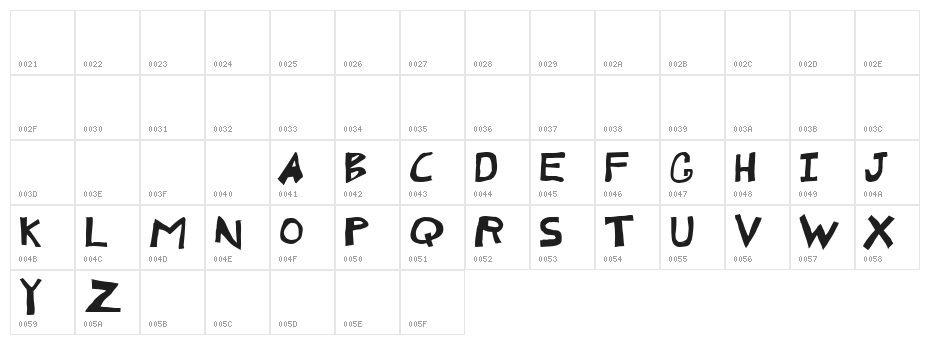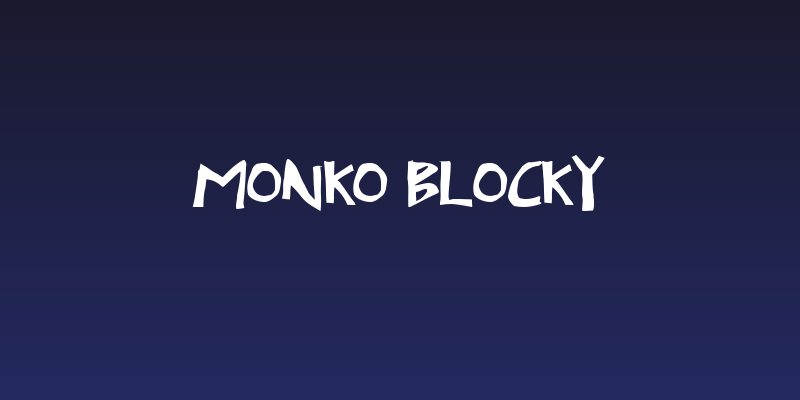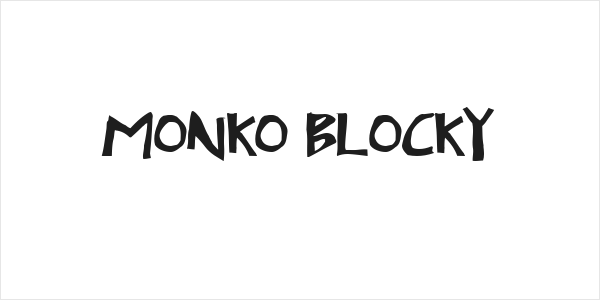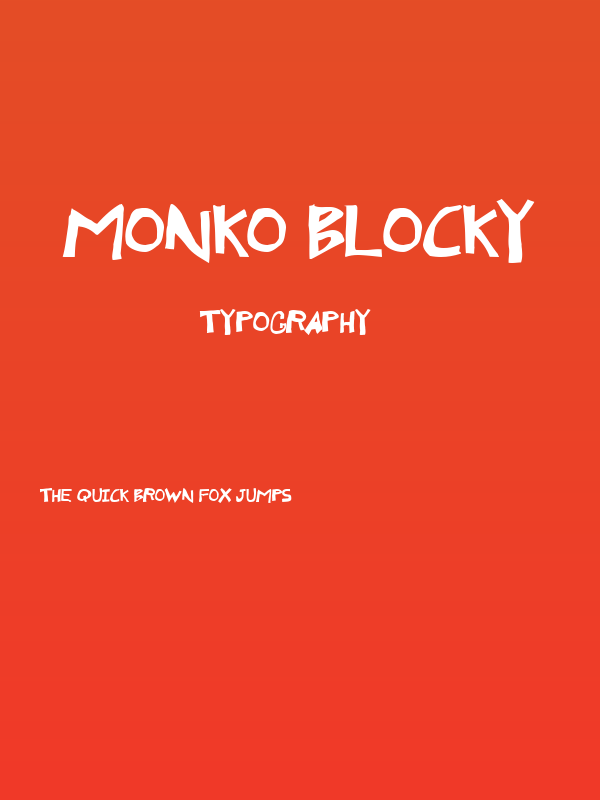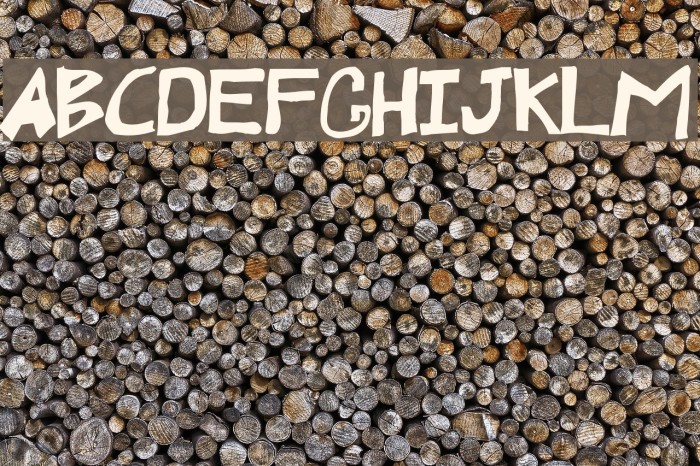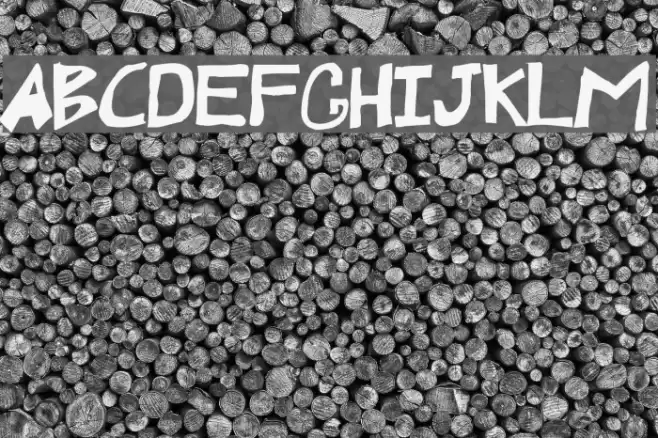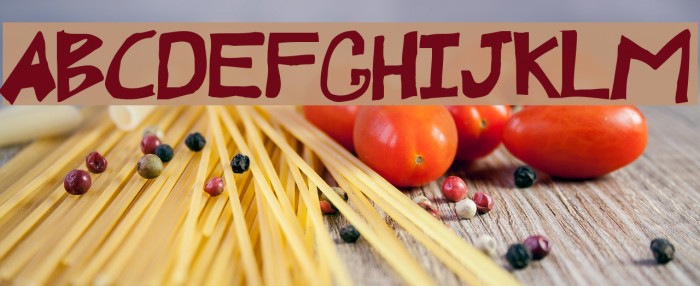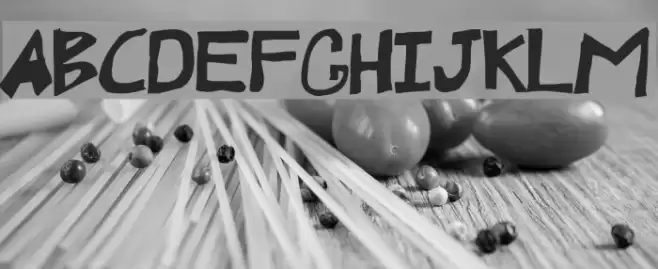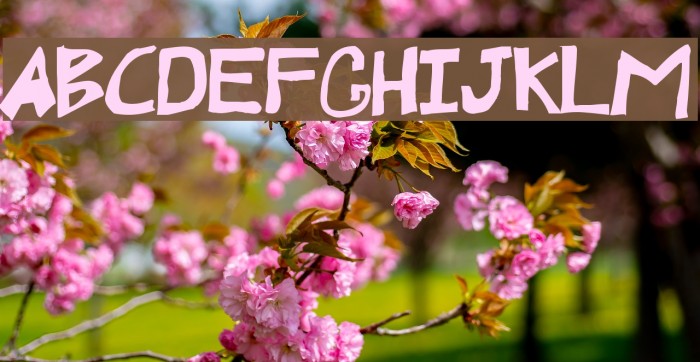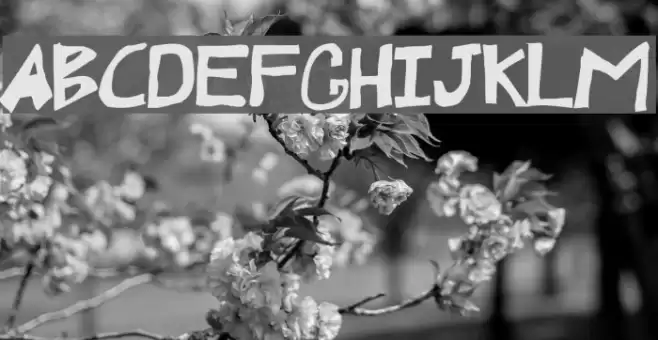
Monko Blocky Font
| Stile generale | Playful, Quirky |
| Caso d'uso | Headlines, Posters, Branding |
| Progetti proposti | Perfect for children's books, comic strips, playful branding, and posters. |